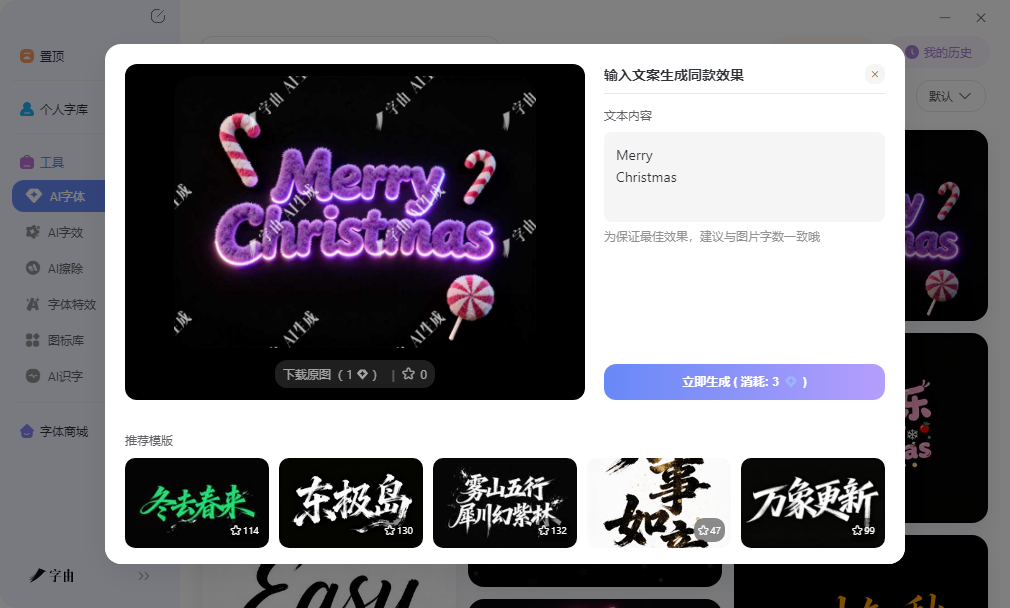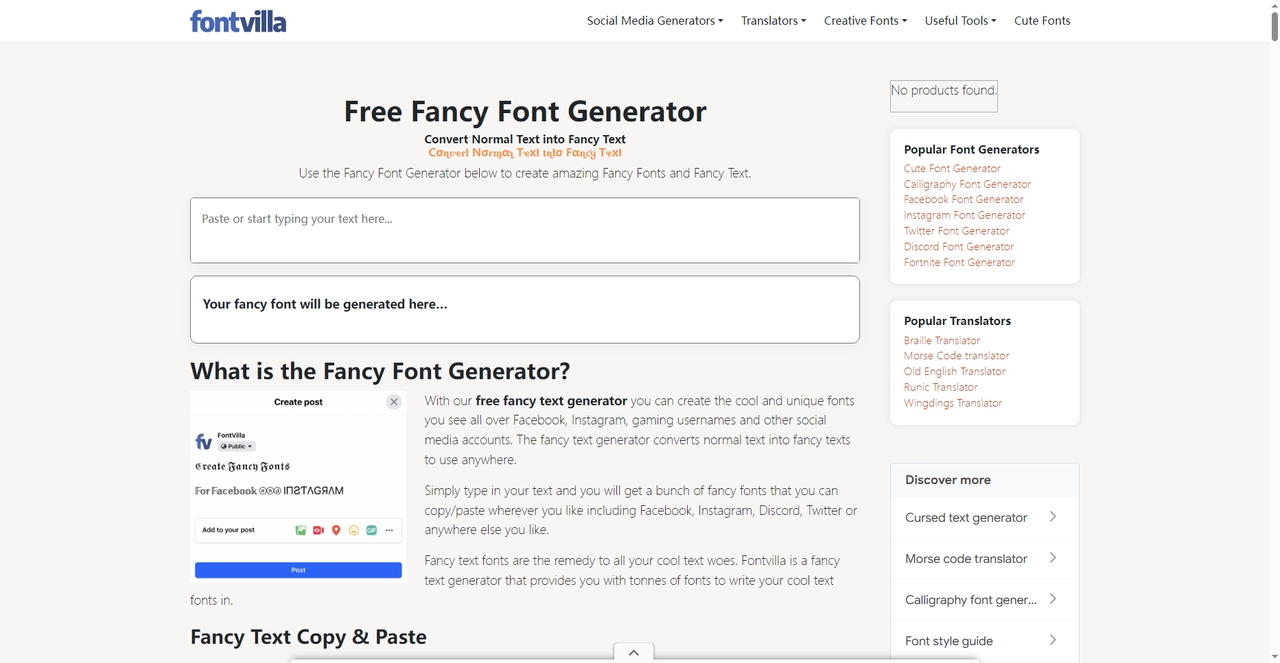
在社交媒体发帖子、写个人简介,或者在PPT里做英文标题,系统默认的久了确实单调。想换点有设计感的字体,但又不想为了几个字打开Photoshop调图层样式。其实有不少工具可以直接把普通英文文本转换成装饰字体,复制粘贴就能用,不需要安装任何软件。这篇文章分享的五个渠道,从生成图片到转换字符都有。
字由的AI字体功能对英文内容也适用。模板库里不少特效风格支持英文输入,水墨、鎏金、霓虹、火焰、立体金属等方向都能处理英文文案。输入一段英文标题,比如品牌Slogan或者活动主题,大约二十多秒后生成一张带特效的图片,导出格式是PNG,默认透明背景。可以直接拖进PPT里做封面标题,或者放进电商详情页里做促销标签,也可以作为社交媒体配图的主视觉。
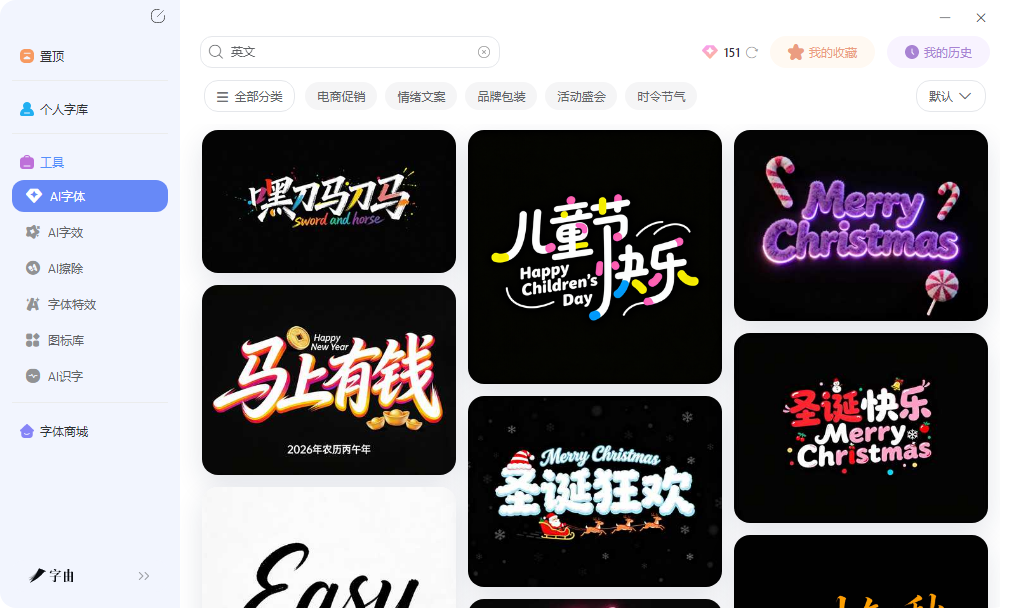
和纯文本转换工具不同,字由产出的是图片,视觉层次更丰富。霓虹模板会让文字边缘带有发光散射效果,金属模板会模拟镜面反射的高光点,水墨模板则会让笔画带有晕染扩散的质感。这些效果是常规字体文件本身不具备的,即使安装了再漂亮的英文字体,在PPT或者Word里打字还是平面的,而AI字体直接给你一张带空间深度的图片。
2、Fontvilla
Fontvilla是一个综合性的英文字体转换平台,收录了超过一百种装饰字体风格。从复古打字机到未来科技,从可爱泡泡到哥特暗黑,风格跨度很大。输入英文文本后,所有风格会同时展示,用户可以并排对比效果,快速找到最匹配项目气质的那一款。
作为英文字体转换的渠道,Fontvilla的优势在于风格覆盖广、对比直观。做品牌方案时如果需要在多个风格方向之间快速出概念,这里的并排展示能省去大量试错时间。生成的结果可以直接复制为Unicode文本,也可以生成图片下载,两种输出方式都支持。网站上还提供了字体大小写转换、文字反转等附加功能,对需要批量处理文本格式的用户来说比较实用。
3、Stylish Fonts Generators
Stylish Fonts Generators提供了多种时尚装饰字体风格。输入英文文本后,系统会列出十几种不同的转换结果,包括粗体、斜体、花体、双线体、空心体等。用户可以逐行浏览,找到最符合自己需求的那一款,点击复制即可。
作为英文字体转换的工具,它的优势在于选择多、生成快。和单一样式的转换器不同,这里一次性给出多种变体,省去了逐个试的麻烦。生成的装饰字符基于Unicode标准,在大多数平台上都能正常显示。对于做社交媒体运营、需要频繁更换字体风格来吸引注意力的人来说,这里的批量转换比较高效。网站上还提供了反向转换功能,可以把装饰字符还原为普通文本,方便后续编辑。
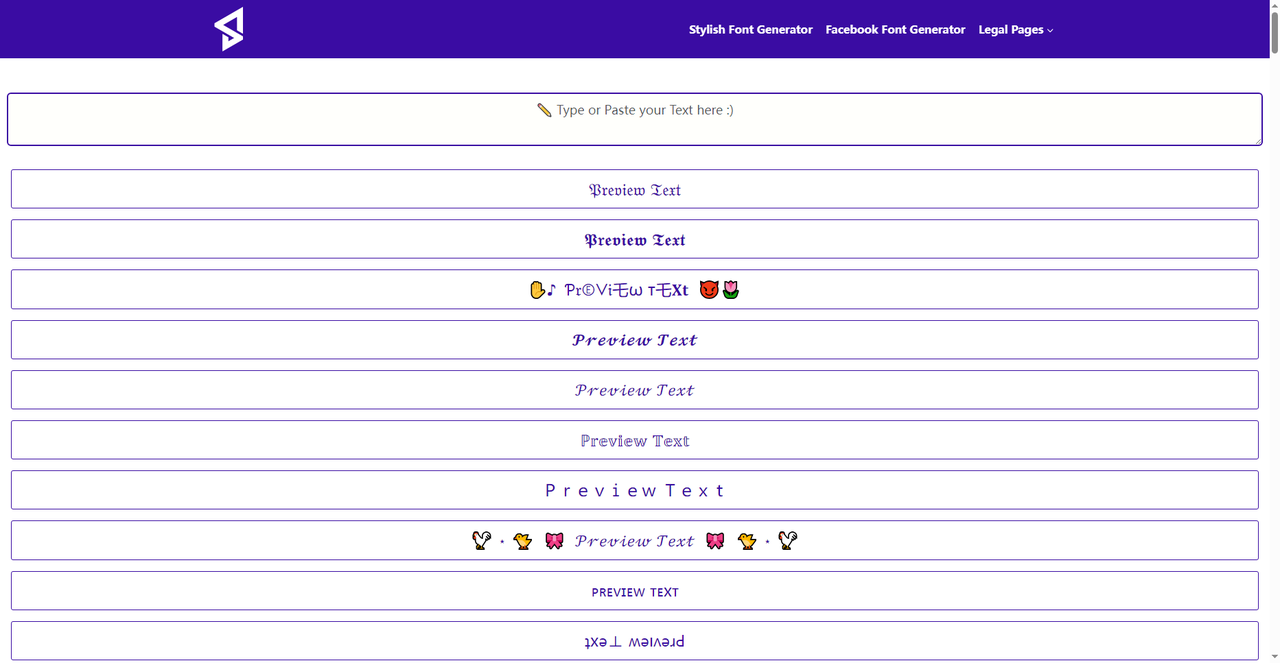
4、Cursive Text Generator
Cursive Text Generator是一个专注草书体转换的在线工具。输入普通英文文本后,系统会转换为手写草书风格的Unicode字符,可以直接复制粘贴到社交媒体、聊天软件或者文档中使用。这种草书体模仿了连笔书写的自然感,适合做婚礼请柬、品牌标语、个人签名等需要优雅气质的场合。
作为英文字体转换的渠道,它的优势在于风格统一、操作简单。不需要生成图片文件,直接复制特殊字符就能用,后续想修改文字内容直接编辑即可。生成的草书字符在Instagram、Twitter、Facebook等主流社交平台上都能正常显示,不会被自动转换为普通字体。对于需要快速发一条带手写感的英文内容的人来说,这个工具比较实用。
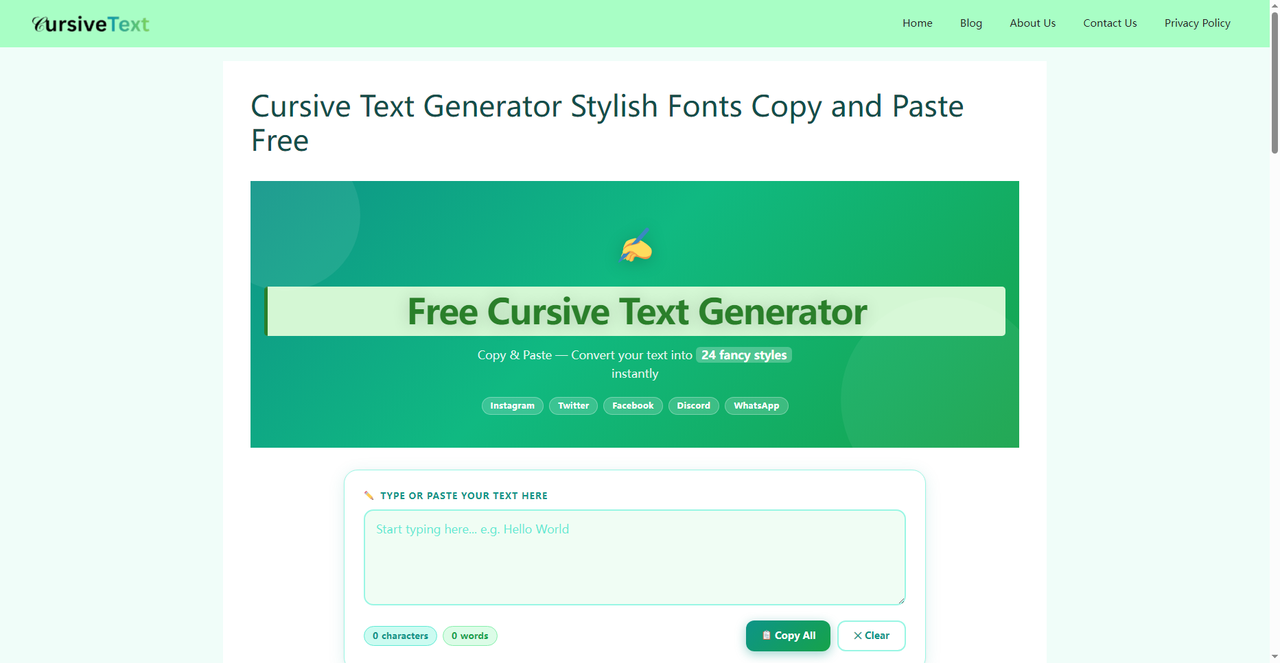
5、Font-Generator
Font-Generator 是一个免费字体生成器,目前收录了超过一千种字体样式。网站的操作流程比较直接,在输入框里打字,下方会实时列出所有可用的文字变体,点击喜欢的样式旁边的复制按钮就能直接粘贴到目标位置。
这个工具对需要快速获得装饰性文字效果的用户比较友好。它支持两种输出方式,一种是复制为Unicode字符,可以直接粘贴到社交媒体、聊天软件或者文档里;另一种是生成PNG图片,可以下载后拖进设计稿中使用。这种双模式输出比较灵活,需要可编辑文字时选Unicode,需要图片素材时选PNG。
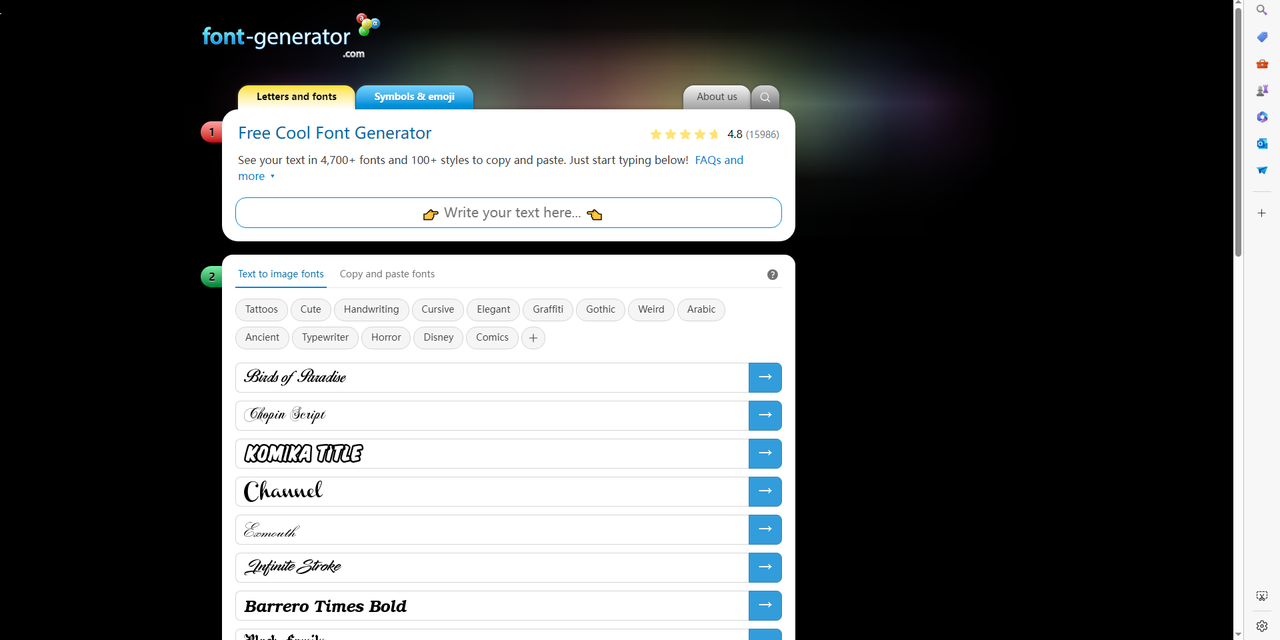
想把普通英文文本变得有设计感,工具选择取决于最终用途。字由的AI字体生成图片,视觉层次最丰富,适合海报标题和电商详情页这类需要视觉冲击力的场景,作为英文字体转换到图片形态的渠道比较实用。Cursive Text Generator的草书体适合优雅场合。Stylish Fonts Generators选择多、生成快,适合社交媒体频繁换风格。Fontvilla风格跨度大,适合品牌方案的多方向探索。